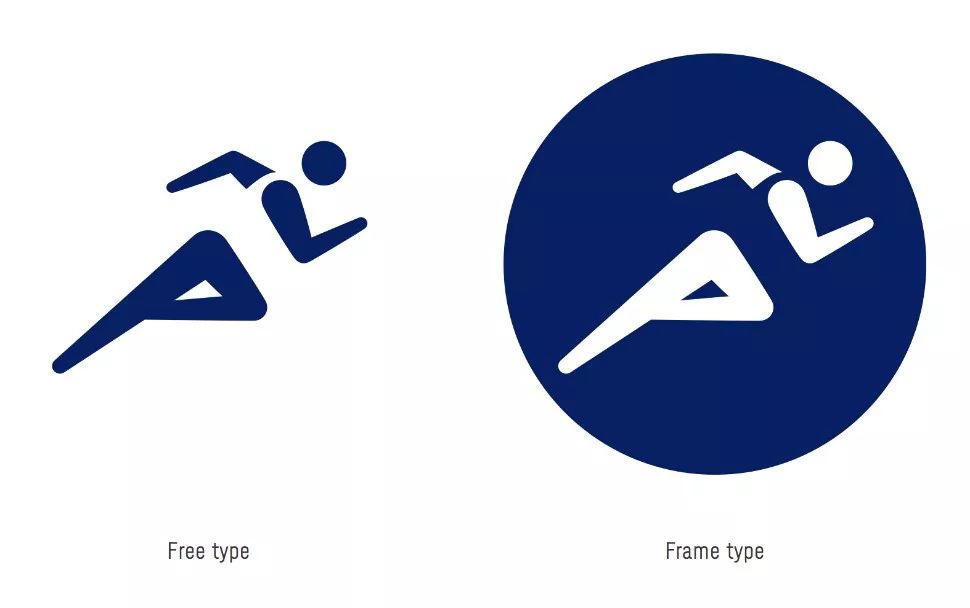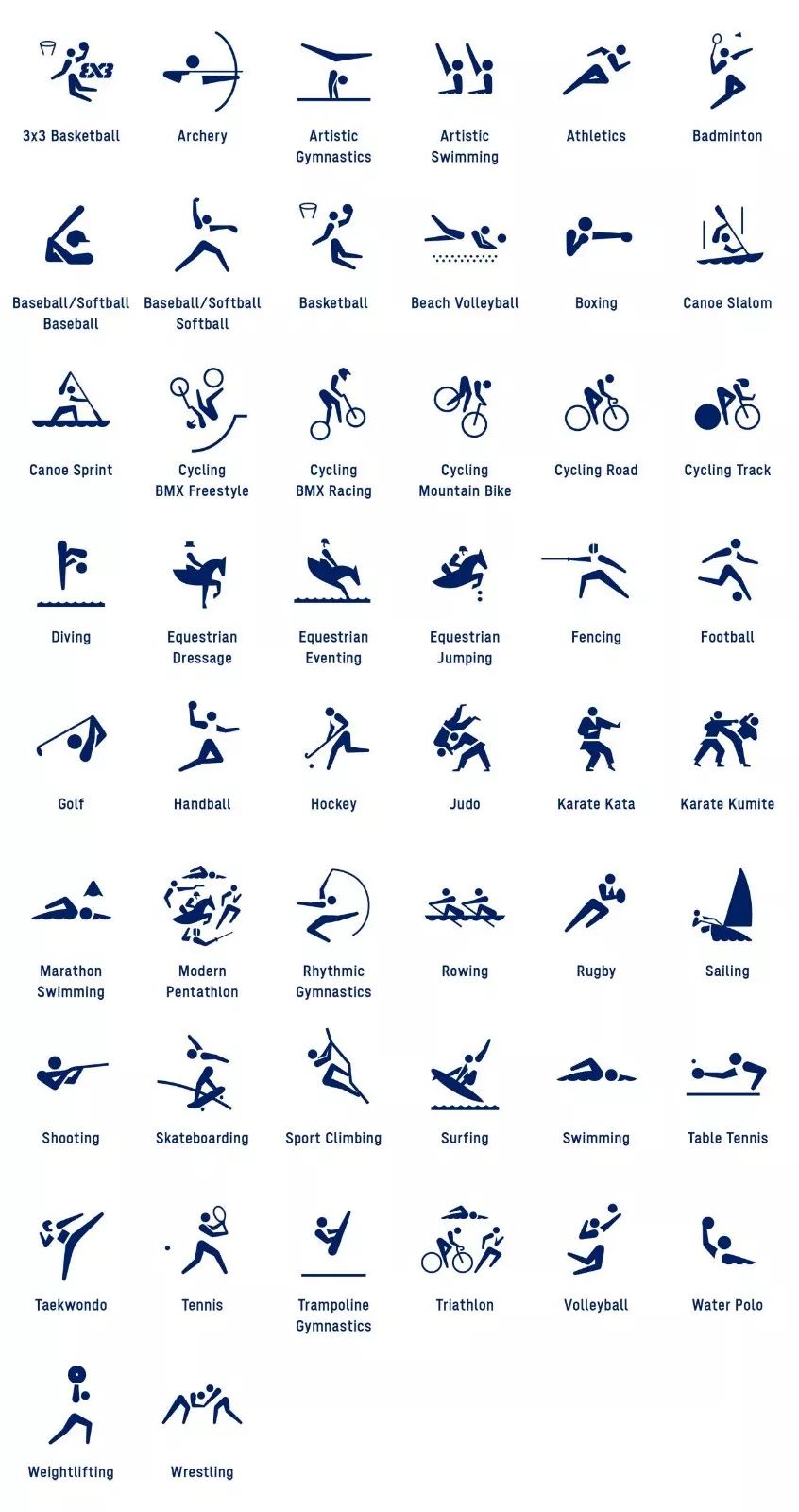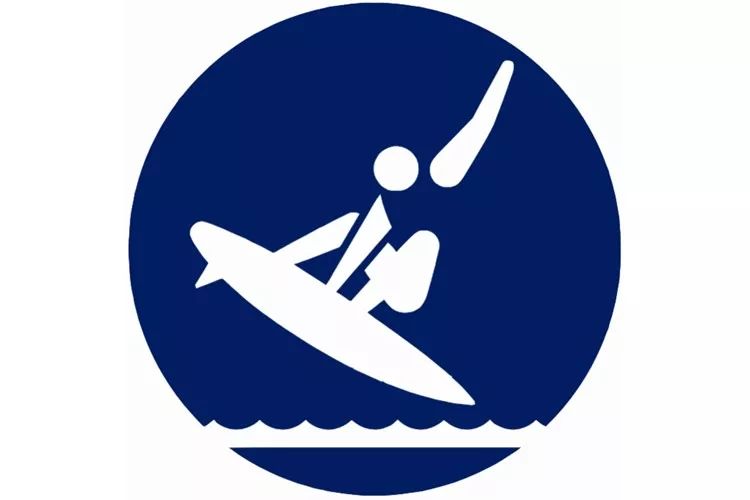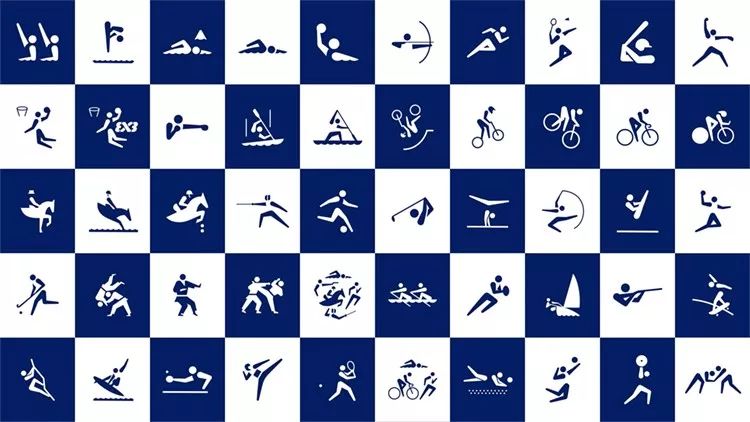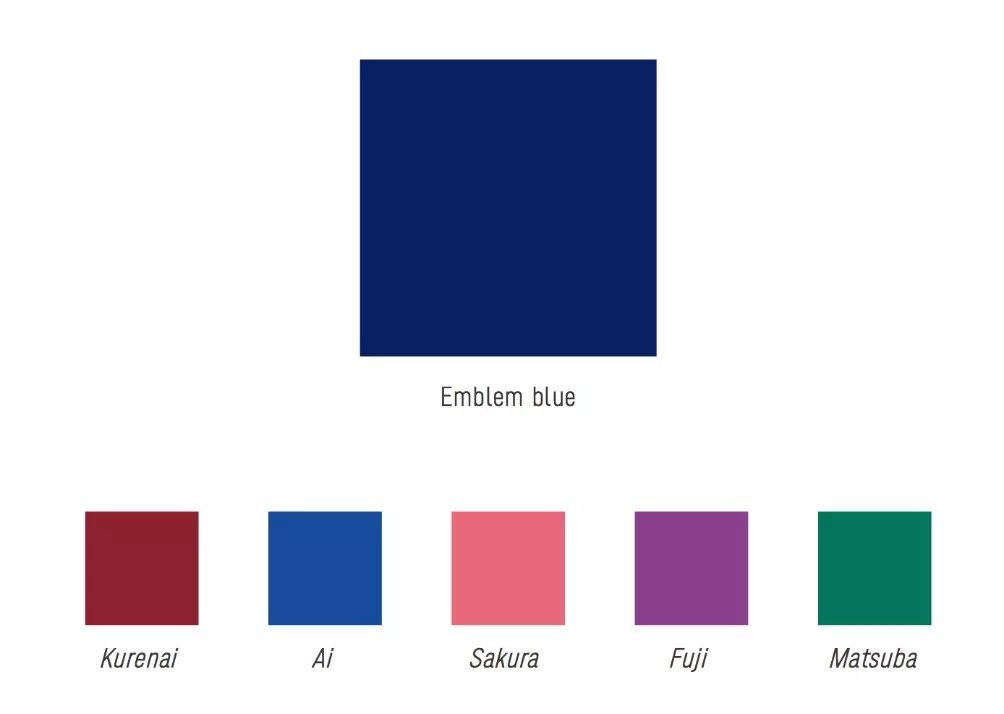
致敬1964!东京奥运会体育图标,广村正彰设计!
今天,东京2020奥运会和残奥会组委会发布了2020年东京奥运会竞技体育图标。根据“和谐创新”的东京2020品牌承诺,东京2020体育图标巧妙地传递着每个运动项目的特点,并在艺术上突出了运动员的活力。
奥运会体育图标早在1948年伦敦奥运会上就有少量使用,而在1964年东京奥运会上正式推出了一套图标系统。1964年,艺术指导Masasa Katzoumie和设计师Yoshiro Yamashita共同设计了那一届奥运会的图标。
上图是1964年东京奥运会图标系统。有了体育图标,即便语言不通,也能传播信息,这种视觉方式极大地方便了来自世界各地的运动员和观众。从那时起,每届奥运会都有不同版本的体育图标。
东京2020体育图标在致敬前辈的同时,更在1964年的基础上进行了创新,在保持信息传播的前提下,加上了赋有跃动感的运动员动作,以最具吸引力的方式展示了运动员的活力。
东京奥运会计划举办33个运动项目,有些运动项目还不止一个图标,这样共有50个不同的图标,这些图标又分别以两种面貌出现,自由型和蓝圆型。
自由型图标将用于海报、门票和许可产品,蓝圆型图标将用于地图、比赛场地标识、比赛指南和网站等更多的用途。
图标色彩主要采用东京奥运LOGO的蓝色,以及另外五种日本传统色作辅助色:Kurenai、Ai、Sakura、Fuji和Matsuba。
东京奥运体育图标的设计,来自日本著名设计师广村正彰(Masaaki Hiromura)领导的团队。
广村正彰表示:“参加东京2020体育图标设计真是一种荣幸。我试图通过这些象形图标来展现运动员的动态美,同时向前辈们在1964年奥运会留下的设计遗产致敬。这些图标用了近两年的时间完成,这融入了很多人的智慧。我希望这些象形图标能够激发每个人的兴趣,并帮助激发东京奥运的每一项运动,并且装点整个东京2020年奥运会。”